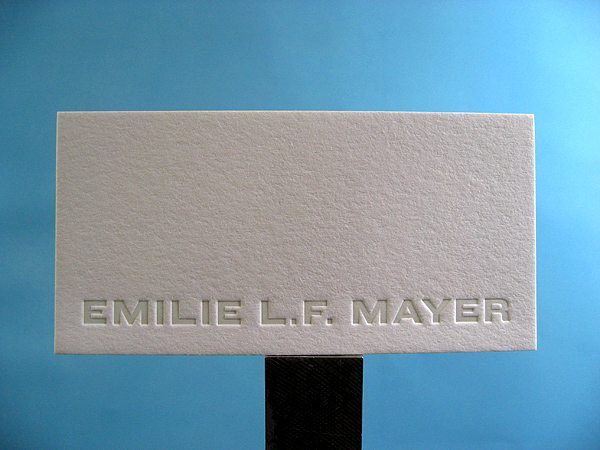
Blindgeprägte Helvetica Bold sieht zu mager aus. Was tun?
wir haben einen Schriftzug blindprägen lassen, der in der Helvetica Neue Bold gesetzt wurde.
Allerdings sind wir mit dem Ergebnis nicht 100%ig zufrieden, da der erhabene Teil der Prägung schmaler aussieht als der jeweilige Buchstabe eigentlich ist. Der gesamte Schriftzug sieht einfach magerer aus als die Helvetica Neue Bold tatsächlich ist.
Ein Arbeitskollege meinte, dass er früher einzelne Schriftschnitte mit Fontographer schnell und einfach interpoliert hätte. Allerdings hat er das Programm seit Jahren nicht mehr benutzt. Ich kenn mich mit Fontographer gar nicht aus.
Was würdet Ihr denn in so einem Fall tun? Hat jemand eine Idee? Würdet Ihr die Schrift manuell fetter machen? Welches Programm würde sich da anbieten?
1. einen fetteren Schnitt verwenden
oder
2. den fertigen Text in Kurven konvertieren, und diesem eine Kontur zuweisen und davon dann das Präge-Klischee fertigen.
Aber nicht an der Schrift mit einem Font-Editor herumbasteln, denn 1. ist das laut Lizenz verboten und 2. gehen dabei oft Font-Eigenschaften wire z.B. die Zurichtung durcheinander.
Wenn du die Schrift fetter als das Original willst, ist es ohnehin keine original Helvetica mehr.
Also kannst du gleich eine der Helvetica ähnliche Schrift verwenden, deren Strichstärke deinen Vorstellungen entspricht. Es gibt genug Schriften, die da passen dürften.
Danke für die Antworten. Eine andere Schriftart oder einfetterer Schnitt (85 Heavy) sind eigentlich keine Optionen da es sich um einen Logo-Schriftzug handelt. Er sollte einfach seinen ursprünglichen Charakter auch als Blindprägung haben.
Was würdet Ihr denn in so einem Fall tun? Hat jemand eine Idee? Würdet Ihr die Schrift manuell fetter machen?
Wenn durch die Blindprägung eine Ausdünnung entsteht und der Hersteller der Prägung das nicht selbst ausgleichen kann, dann klar: dann würde man eine Umrisslinie zur Originalzeichnung hinzufügen und dies so ausgleichen. Das kann jedes Vektor-Illustrationsprogramm. Mit den Fontdateien muss man da gar nicht rumspielen.
Wenn durch die Blindprägung eine Ausdünnung entsteht und der Hersteller der Prägung das nicht selbst ausgleichen kann, …
Lese ich da heraus, Du würdest erstmal den Ball zum Hersteller zurückspielen? Wäre ja auch eine Option.
Eine Prägung mit vertiefter Form wäre hier ev. angebracht. Bei dieser Art sieht die Schrift dann dem Original änlicher, da keine Verdünnung erfolgt.
Bei einer erhabenen Blindprägung wird ein Teil der in der Vorlage sichtbaren Linie zur Schulterfläche, dadurch werden die Linien dünner und müssen entsprechend verdickt angelegt werden. Wieviel dicker die Linie werden muß, hängt von der Ausführung ab. Eine tiefe gravierte und bombierte Messingform mit gegossener Patritze pägt detailreicher, genauer und zierlicher als eine gestufte Prägung von geätztem Werkzeug. Ich kenne die Wirkung aus der Umkehrung. Wenn ich feine Schriften für eine Prägung anlege, lege ich in InDesign eine Kontur um die Buchstaben, und das sieht im PDF in schwarzer Farbe grausam aus. Umso größer die Freude, wenn aus einer 0,4 mm fetten Linie Mindeststrichstärke für die Gravur eine feine und zarte erhabene Linie geworden ist, weil die umgelegte Kontur in der Schulterfläche unsichtbar wird. Die Wirkung ist auch ein wenig vom Papier abhängig. Man kann das bei Schrift einfach mit dem Font in InDesign machen, ohne Umwandlung in Pfade.
Erwin Krump stimme ich zu: die vertiefte Blindprägung ohne Patritze ergibt keinen Strichstärkenverlust. Ist freilich weniger beeindruckend als das erhabene Relief.
Eine Prägung mit vertiefter Form wäre hier ev. angebracht. Bei dieser Art sieht die Schrift dann dem Original änlicher, da keine Verdünnung erfolgt.
kannst du das genauer erläutern, ich kann mir das gerade nicht vorstellen.
Erhabene Blindprägung, Papier wird zwischen Matrize und Patrize verformt: http://www.druckerey.de/tl_files/druckerey/startseite-galerie/Joyce1.jpg
Vertiefte Blindprägung, stempelartige Hochdruckform aus Metall wird in das Papier gepreßt, mit oder ohne Farbe: http://www.druckerey.de/tl_files/druckerey/startseite-galerie/EmilieMayer1.jpg
Doch, eben dort. Wo das Papier zwischen zwei Formen gepreßt wird, entsteht der Verlust innerhalb der Strichstärke der Vorlage. Die vertiefte Prägung wird wie ein Stempel ins Papier gepreßt, die schrägen Flächen entstehen außerhalb der Druckvorlage.
Nur zur Vollständigkeit:
Kein Formverlust entsteht nur bei einer tiefgeprägten Form, wenn das Prägeklischee eine Positivform oder auch mit einer gesetzten Prägeschrift (härtere Legierung, Satz durch den Buchbinder) wie im Buchdruck, nur mit starkem Druck auf den Buchdeckel oder auf sonstige Träger geprägt wird.
Dies ist die einfachste und kostengünstigste Art der Prägung.
Füher wurden die Matrizen der Zeitung nach diesem Prinzip hergestellt.